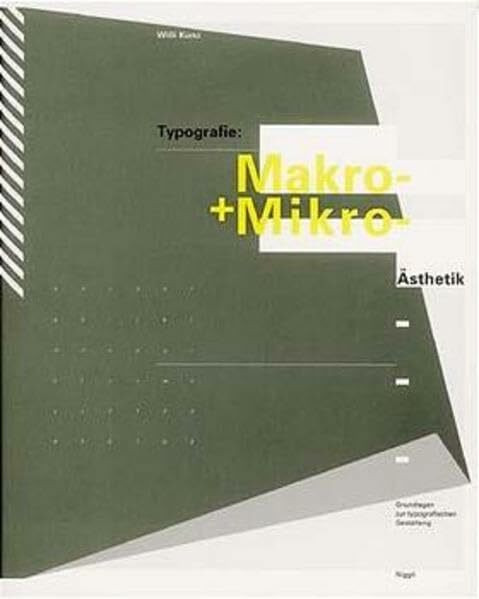
Typografie: Makro- und Mikroästhetik: Grundlagen zur typografischen Gestaltung
Dieses Buch zeigt die Anwendung von Theorie in der Praxis und dient als Lehrmittel für alle, die im Bereich der visuellen Kommunikation tätig sind. Indem es die Rolle der typografischen Gestaltung in der heutigen, von Medien dominierten Umwelt analytisch betrachtet, vermittelt es eine kritische Einschätzung nicht nur des in der Gestaltung Vordergründigen, sondern auch der ihr zugrunde liegenden Denkweise. Der erste Teil des Buches befasst sich mit den mikroästhetischen Qualitäten von Buchstaben, Zahlen und Satzzeichen sowie Linien und geometrischen Elementen und ihrer vielfältigen Anwendung. Im zweiten Teil werden die gestalterischen Aspekte von Fläche, Struktur, Sequenz, Kontrast, Form und Gegenform analysiert und mittels ihrer Funktion in der typografischen Gestaltung mit Beispielen aus Unterricht und Praxis illustriert. Im dritten Teil wird anhand von Arbeitsbeispielen gezeigt, wie typografische Elemente auf der mikroästhetischen Ebene zur Gestaltung beitragen. Im vierten Teil schliesslich wird in einer Serie von Architekturplakaten die Verbindung von Konzept, Makrostruktur und Mikroästhetik analysiert. Auszeichnung: 'Die schönsten Schweizer Bücher' 1998